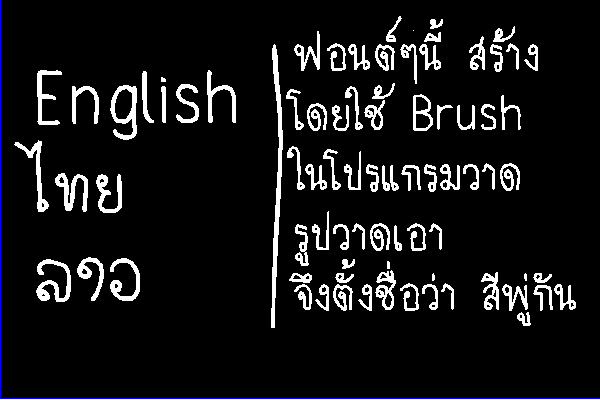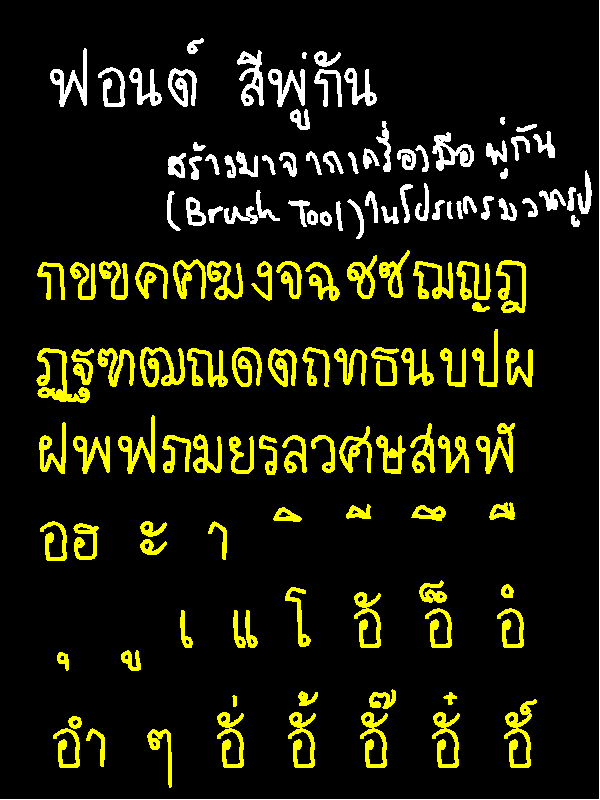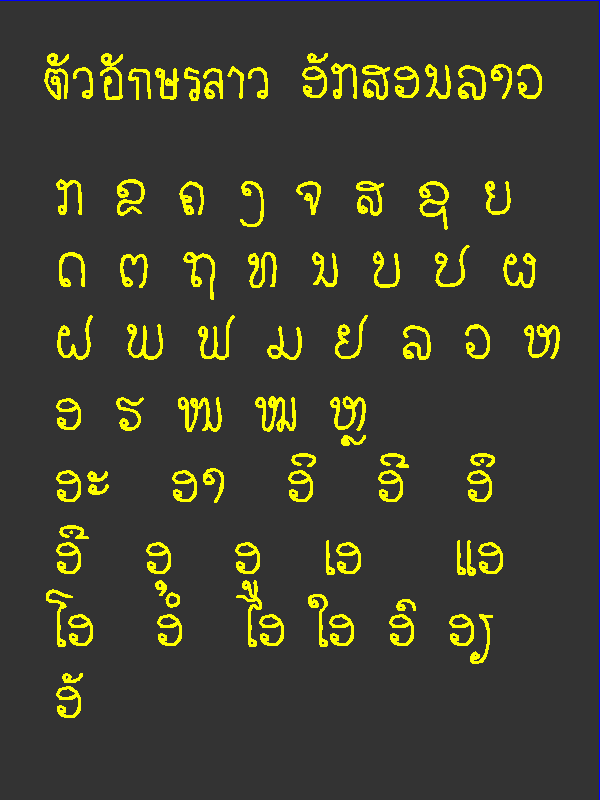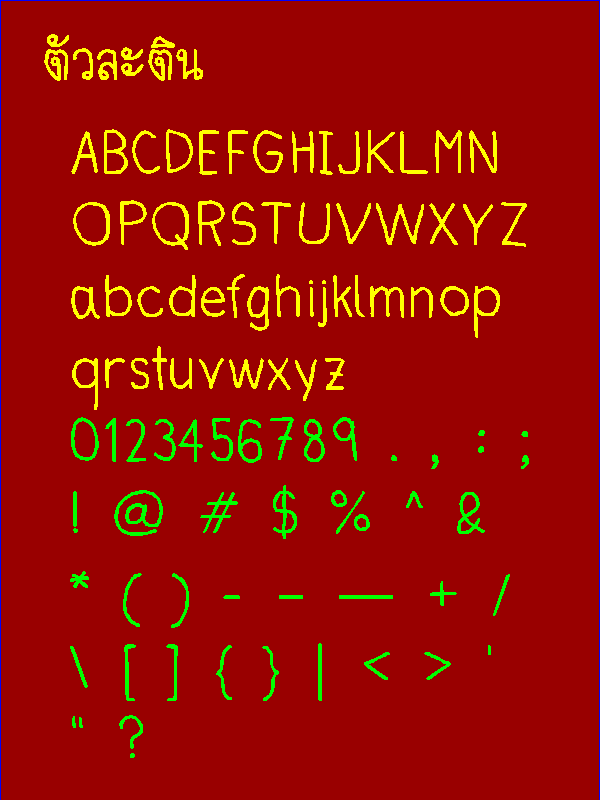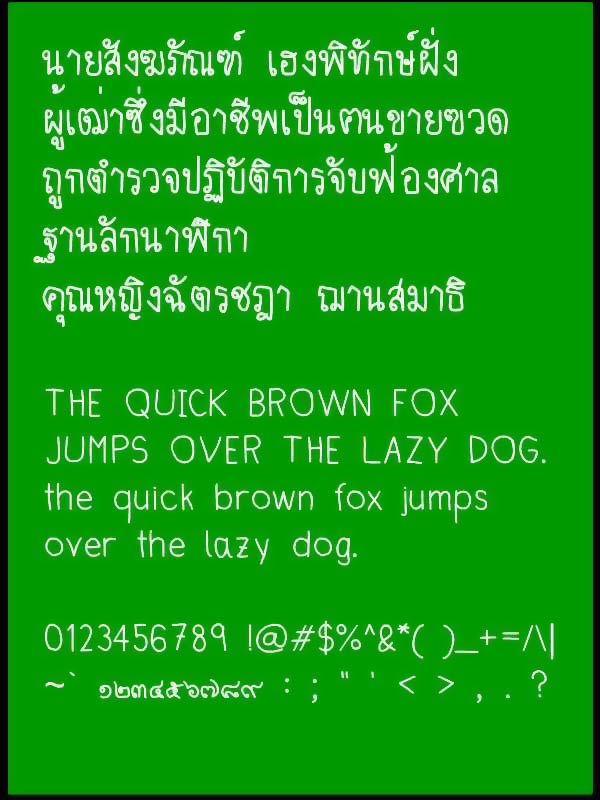
ไปเที่ยวลาวมาครับ แล้วลองศึกษาอักษรลาว อักษรเขมร (อักษรเขมรนี่ดูแป๊บเดียวก็วางแล้ว รู้สึกว่าพลังตัวเองไม่ถึง) เห็นว่าตัวอักษรมันโค้งๆ มนๆ ดี แต่อักษรลาวยังพอได้ ศึกษาไปศึกษามา บวกจากที่ช่วงนี้ว่างจากการเรียน ก็นึกสนุก หยิบคอมมา ทำฟอนต์โลด
ฟอนต์นี้มีตัว อังกฤษ ไทย ลาว ครับ
Sipugun (สีพู่กัน)